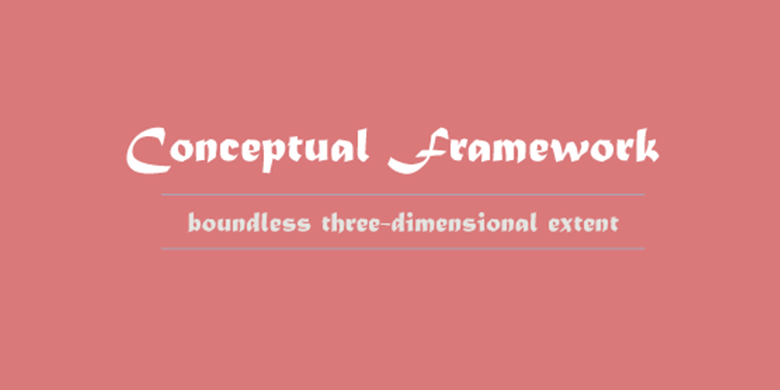
Matura字体由匈牙利木雕和字体设计师imre reiner于1938年设计,Monotype公司发布。马图拉字体是一个大胆的笔迹,看起来像是用一支宽边笔写的。一套充满活力的近乎繁荣的柱头,称为脚本式柱头,扩大了通常的字体范围。Matura独特的线条使其适合于广告使用和文本标题,以及用于卡片、邀请和公告等非正式工作。
Matura font was designed by the Hungarian wood engraver and type designer Imre Reiner in 1938 and released by the Monotype Corporation. Matura font is a bold upright script that looks as if it were written with a broad-edged pen. A set of vibrant near-flourished capitals, called scriptorial capitals, broadens the usual range of script faces. Matura’s distinctive lines make it appropriate for advertising uses as well as text headings, and for informal work like cards, invitations, and announcements.